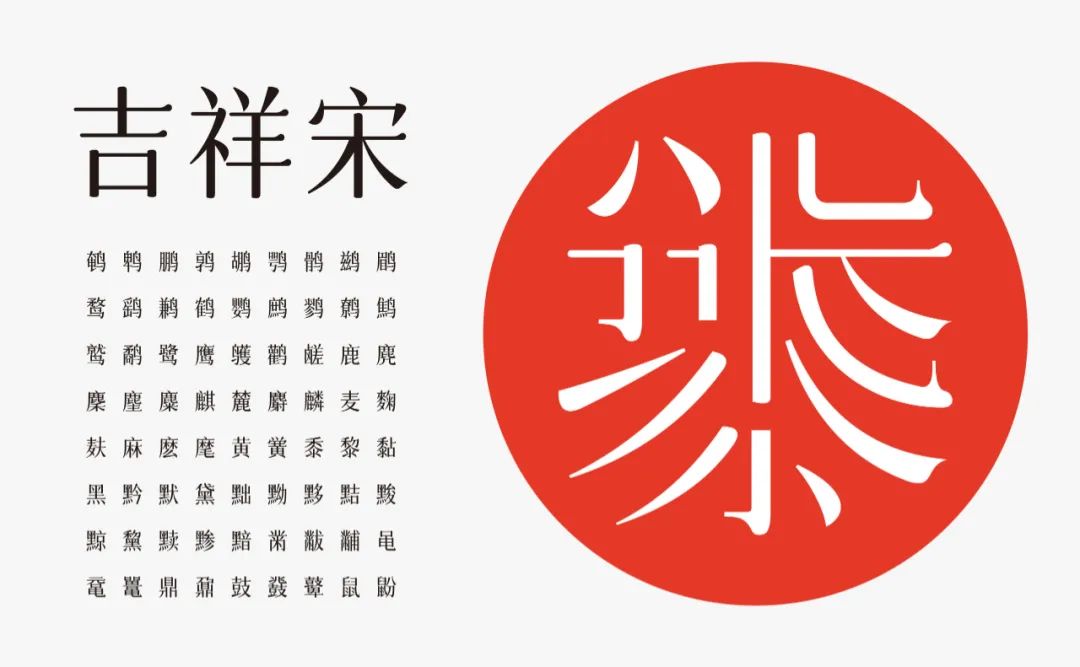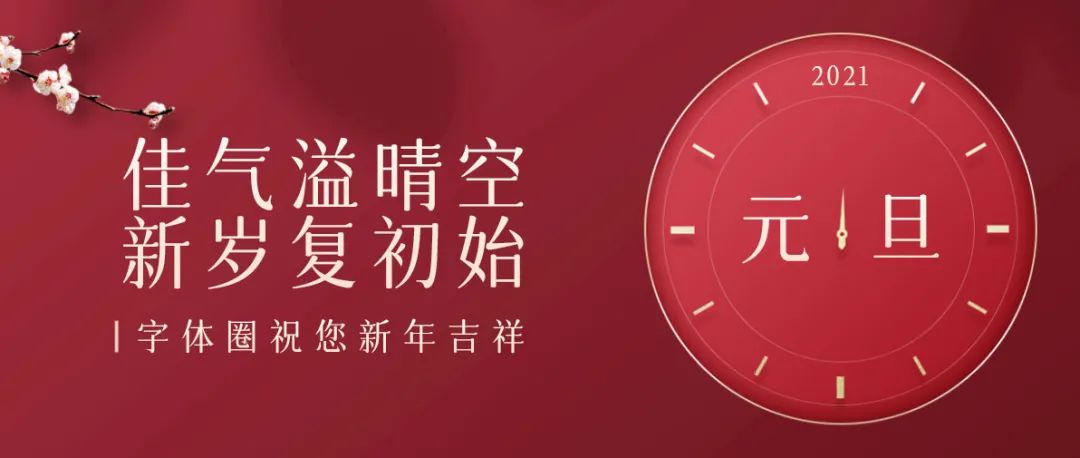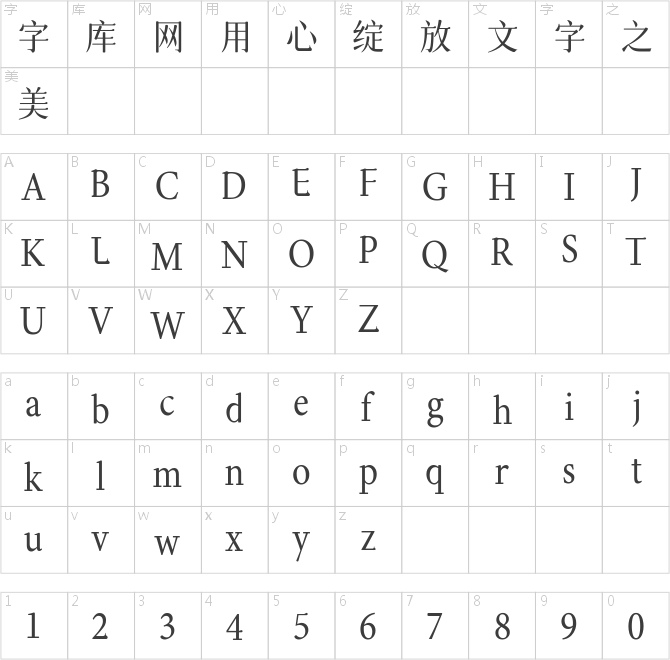
字体圈欣意吉祥宋 详情页
字体名称: 字体圈欣意吉祥
字体圈欣意吉祥宋
这套字涵盖国家GB2312编码标准的6763个中文字符,52个英文字符,10个阿拉伯数字,若干个标点符号,按需添加若干生僻字,共7000余字符。这是一套宋体风格的标题字,风格整体偏圆润古风,目前市场上免费商用的宋体字,除了思源宋体,好像就是思源宋体的修改版,没有专门设计风格的宋体字。
字体命名原本打算跟风格相同,欲名为“润宋体”,但没有什么特殊意义,毕竟免费字体可遇不可求,2020年确实是困难的一年,从年头到年尾非常艰难的度过,后来决定今天发布后,想到两个词“吉祥”与“平安”,纠结了好一会,最终定为“吉祥宋”,全名:字体圈欣意吉祥宋,很优雅的一个名字,我很喜欢,祝您今后每一年都能吉祥如意平安顺遂!